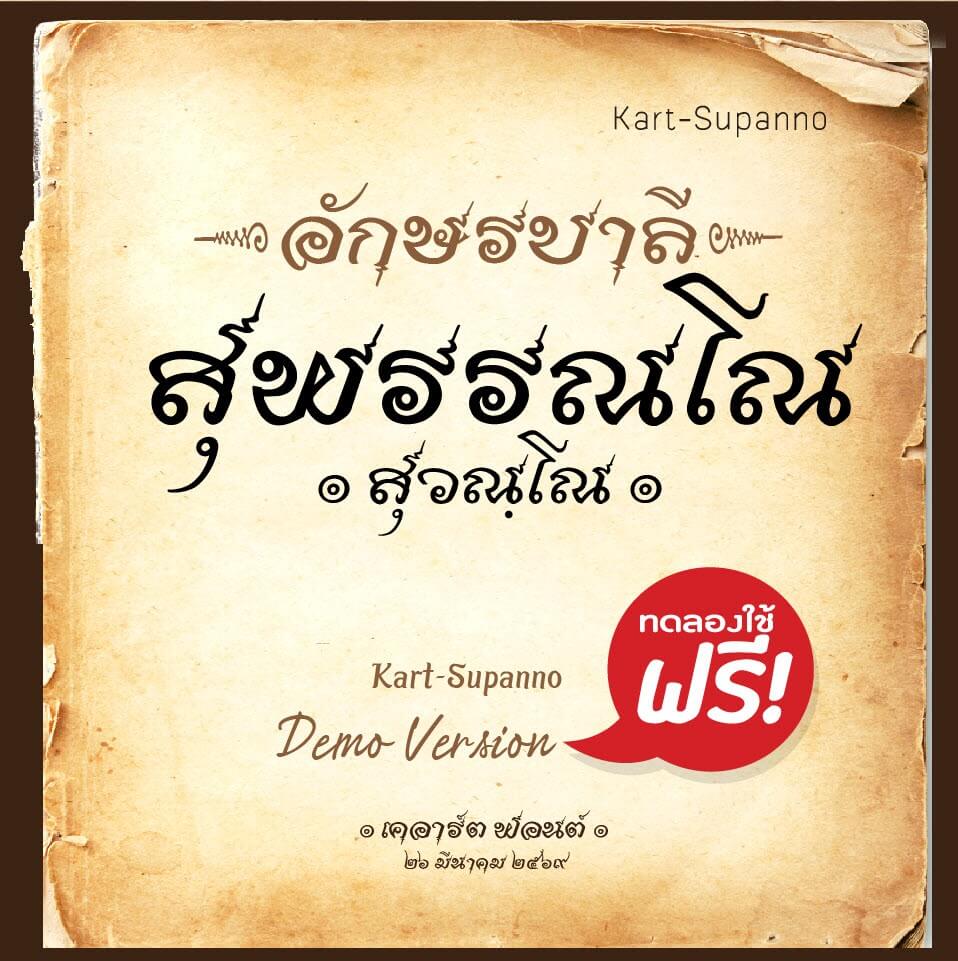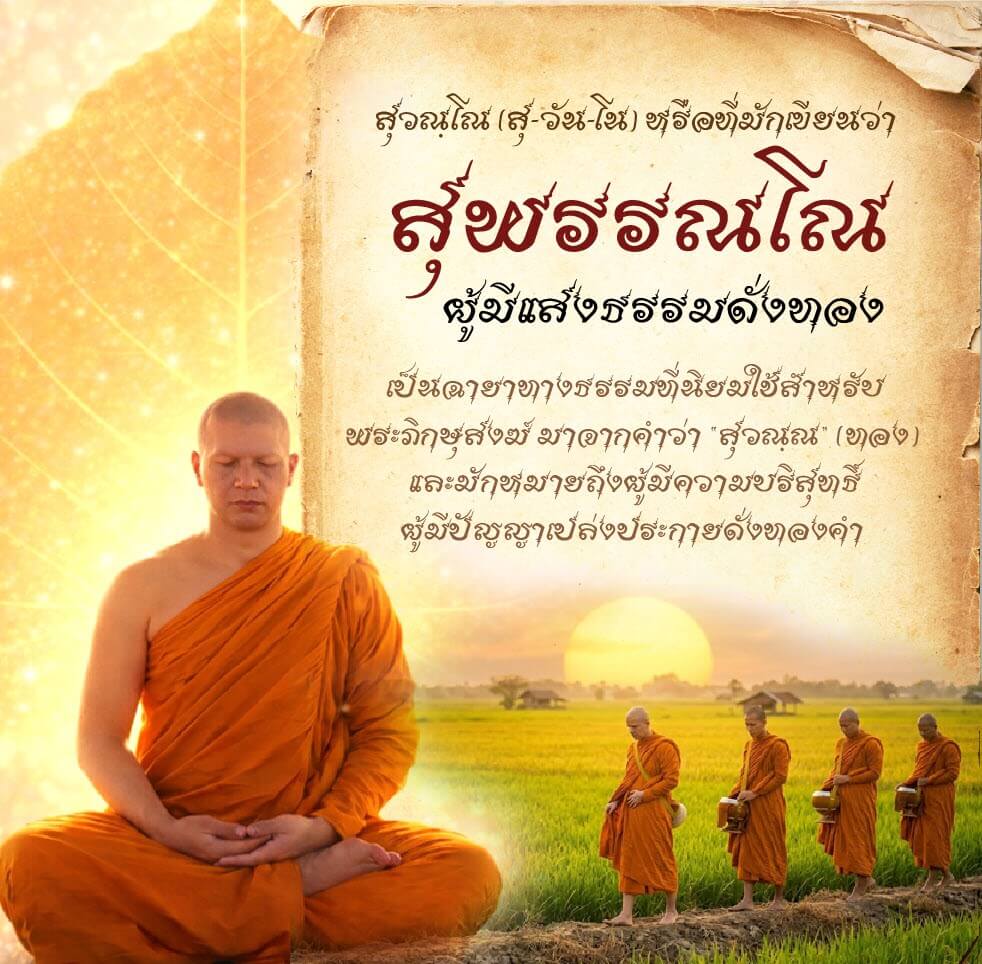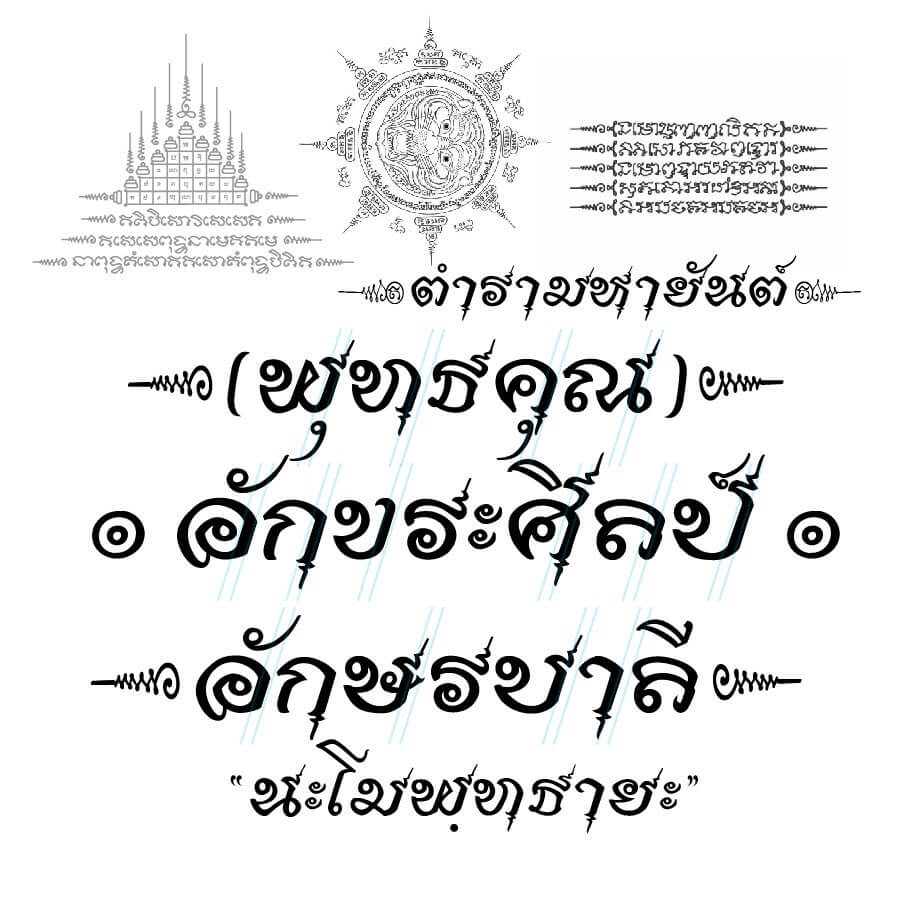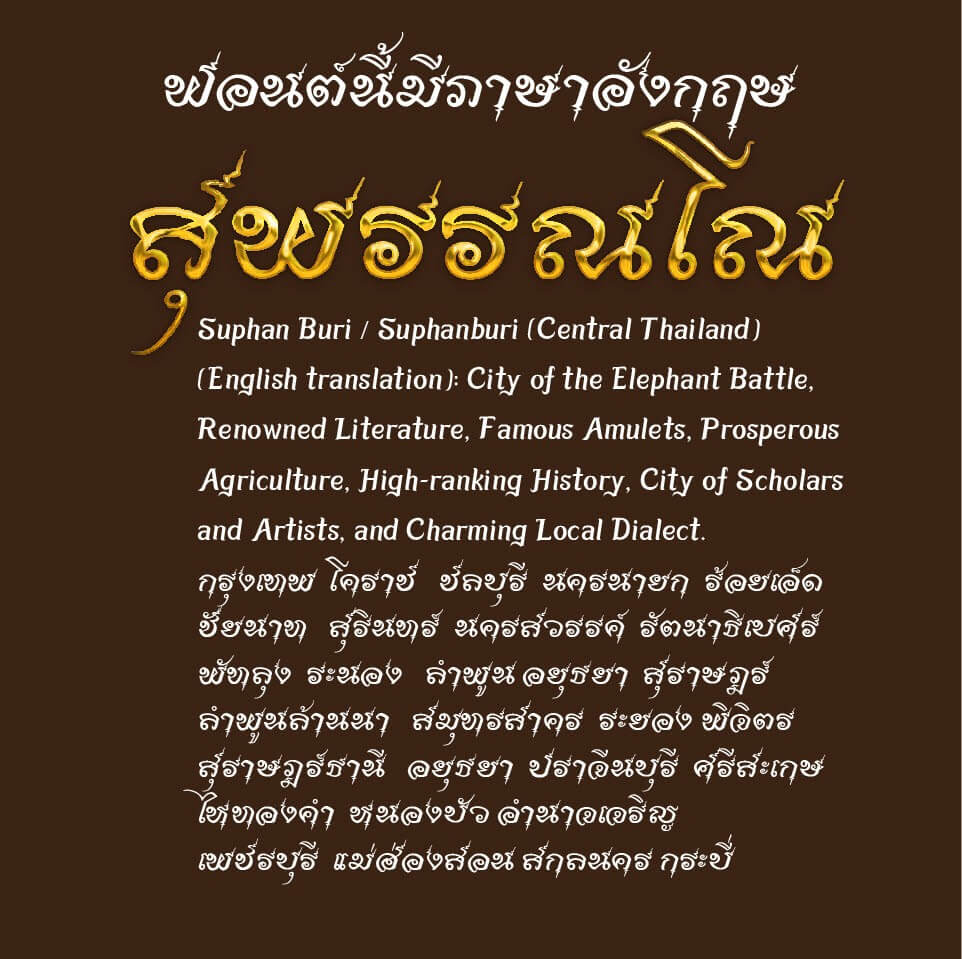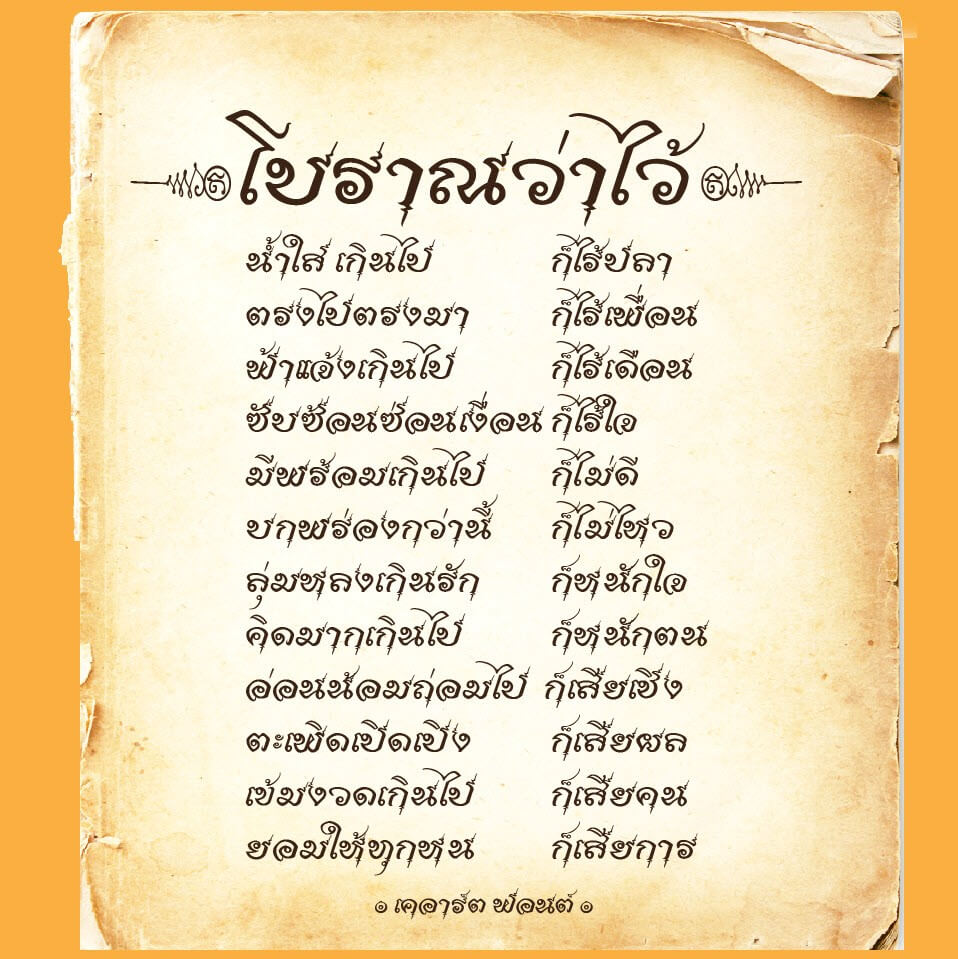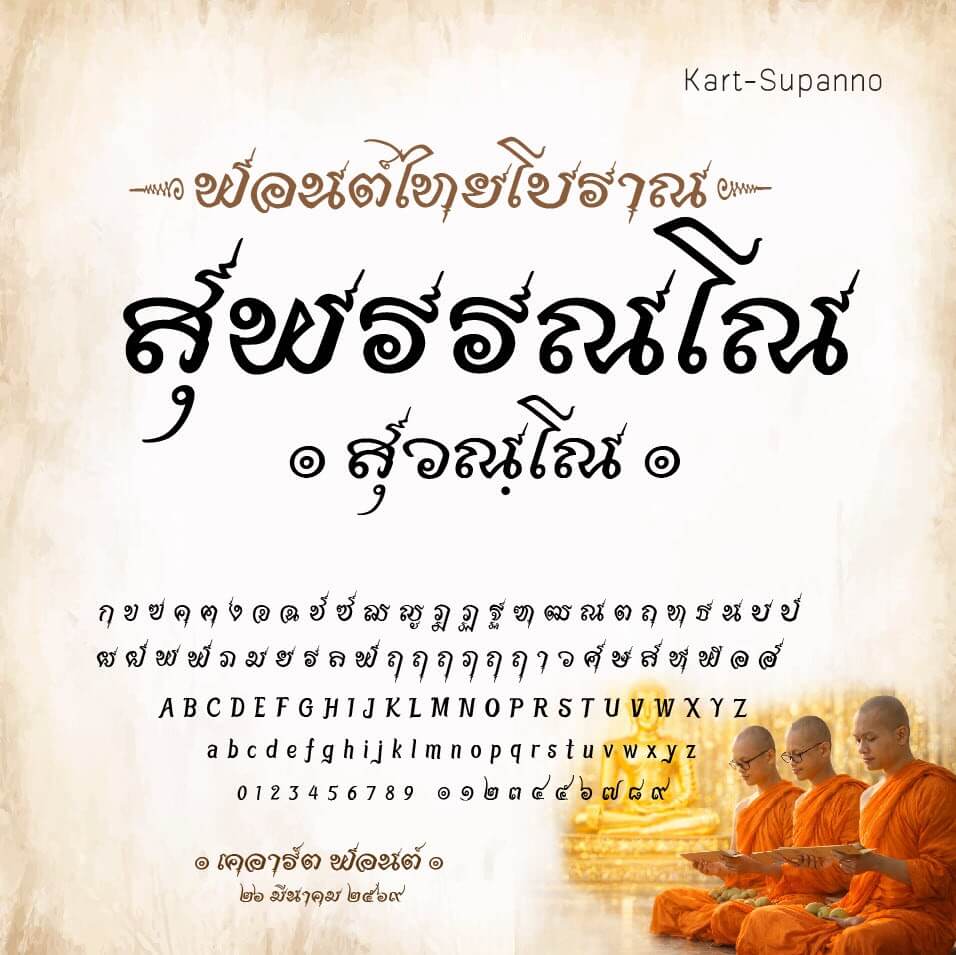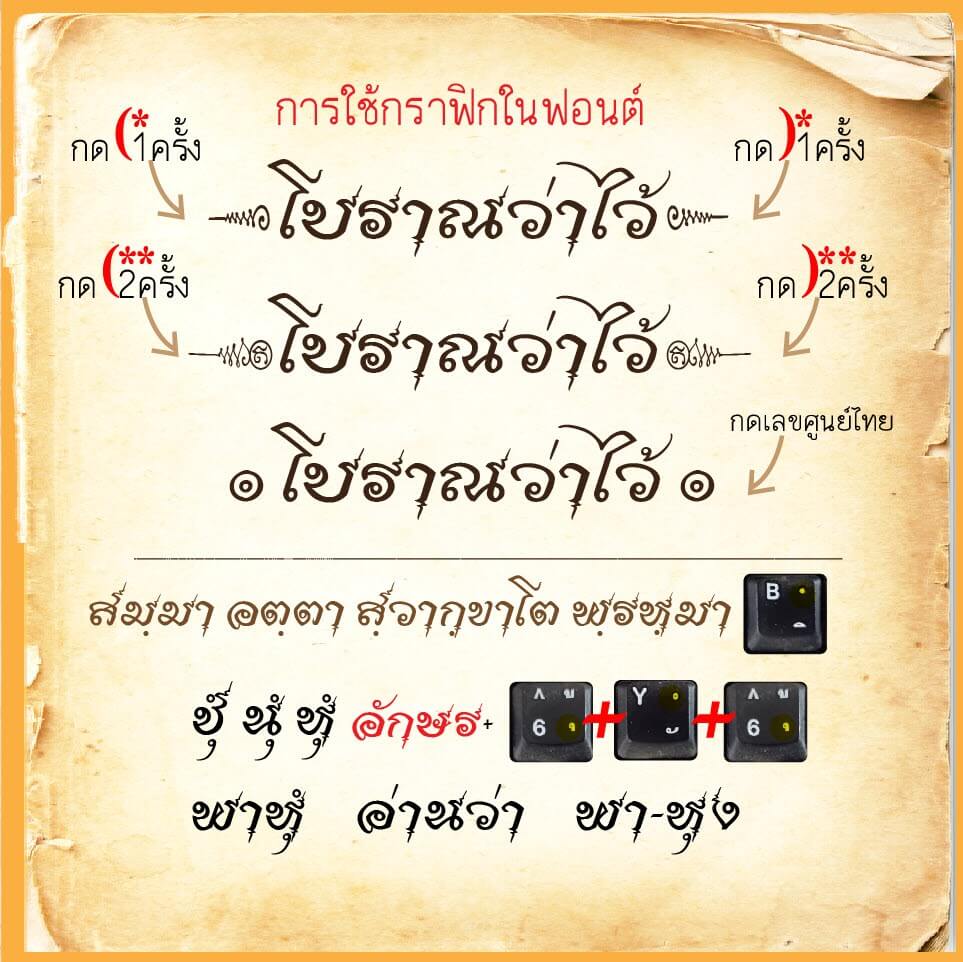
เคอาร์ต-สุพรรณโณ (Kart-Supanno)
ฟอนต์ เคอาร์ต-สุพรรณโณ (Kart-Supanno) – เป็นฟอนต์ที่เขียนโดยได้แรงบันดาลใจจากลายมือเขียนของ อ.จินดา เนื่องจำนงค์  #ฟอนต์บาลี #ฟอนต์ไทยโบราณฟอนต์นี้มีลายกราฟิกอยู่ในฟอนต์ด้วยครับ